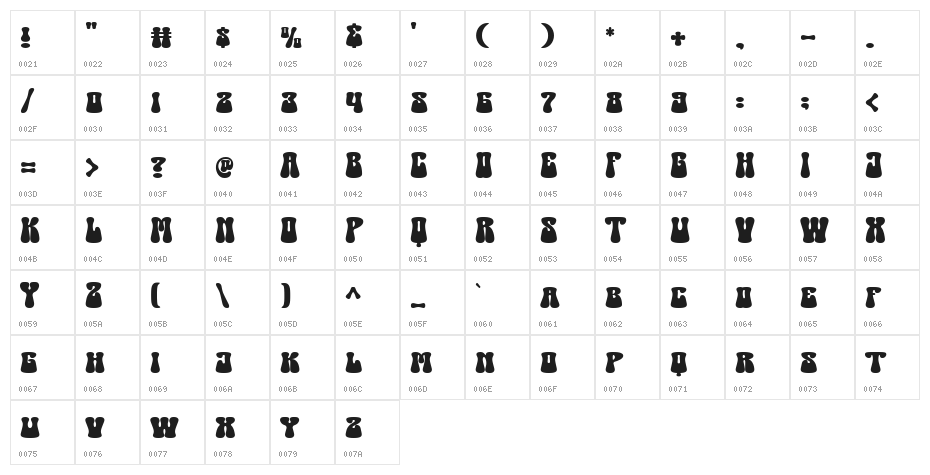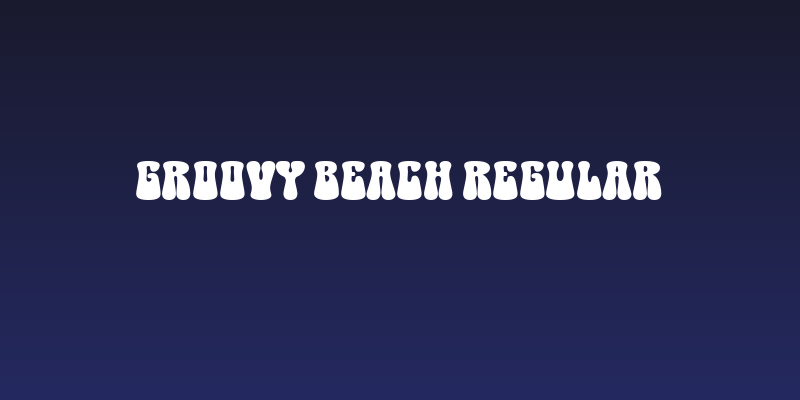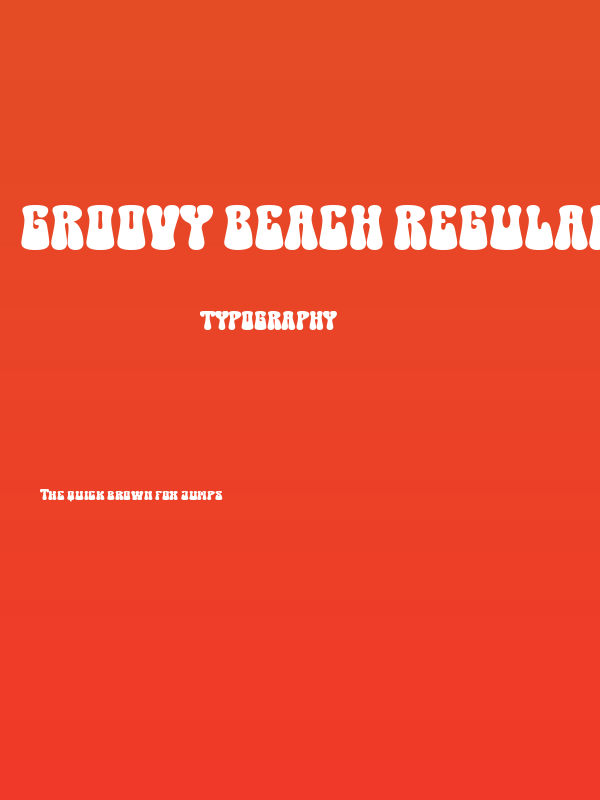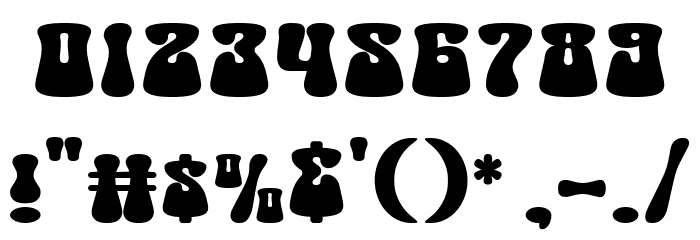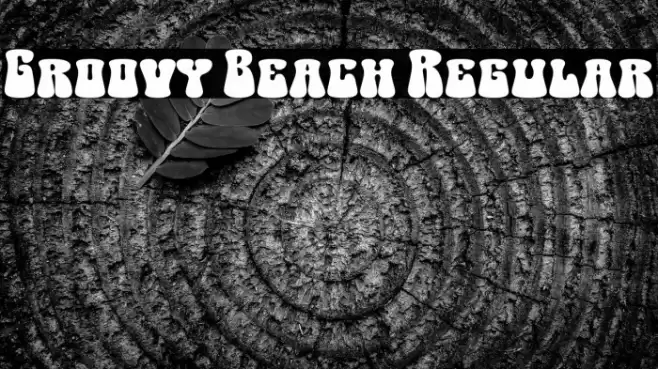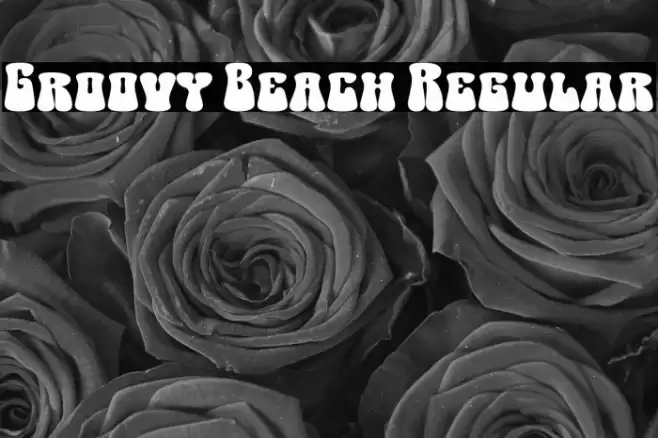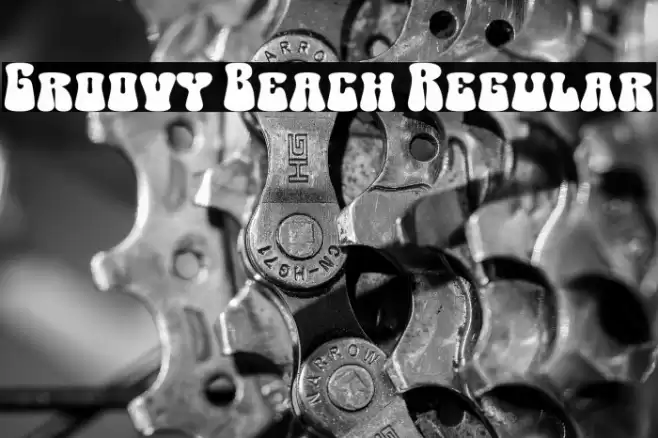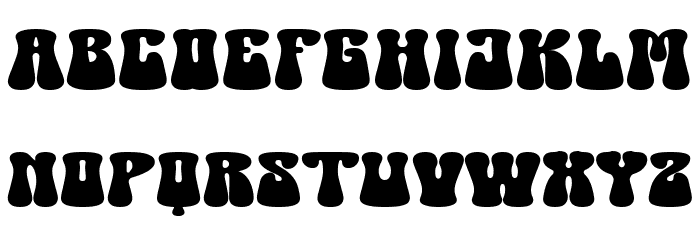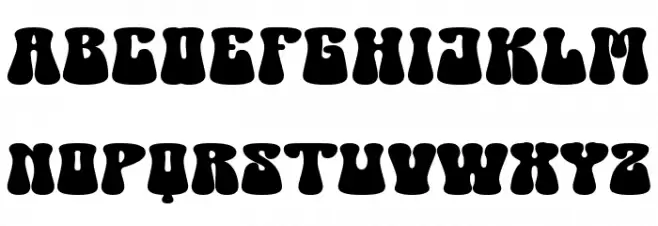
Groovy Beach Regular Font
| Gesamtstil | Vintage |
| Vorgeschlagene Projekte | Ideal for posters, album covers, event flyers, and branding that seeks a vintage or playful theme. |